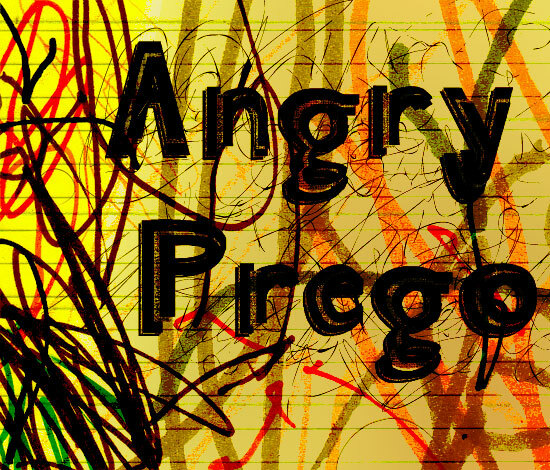
Angry Prego von Vered Gilad Friedman ist eine kostenlose, verzerrte Display-Schrift mit einer unruhigen, handgezeichneten Attitüde. Die Buchstaben wirken wie in Form gezogen und gestaucht, eine Mischung aus massiven dunklen Flächen, versetzten Konturen und kratzigen Bewegungen, die der gesamten Schrift einen spannungsgeladenen, wilden Rhythmus verleihen.
Das macht sie zur idealen Wahl für Plakat-Überschriften, Zine-Cover, Mixtape-Artworks, Titelkarten und rebellisches Branding, bei dem eine kostenlose Schrift lieber roh als sauber wirken darf. Sie funktioniert auch hervorragend für kurze Zitate, Event-Flyer und Cover-Lines, da die vielschichtigen, wackeligen Buchstaben genug visuelles Rauschen mitbringen, um den Look allein zu tragen.